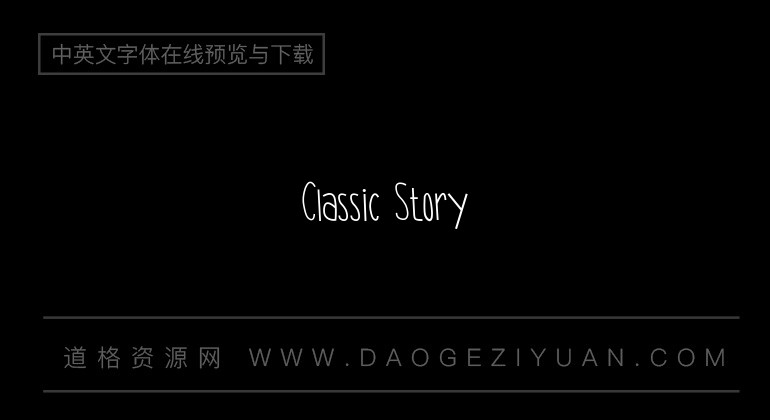
Classic Story 字体是一种优秀的手写风格字体,具有艺术性和可读性。 这种字体具有非常自然的手写风格,每个字母都具有独特的风格和形状,使其非常适合用于各种印刷和数字媒体设计项目。它的字母形状优美、流畅,同时还具有一定的装饰性,能够增强设计的美感和格调。 Classic Story 字体的特点还包括: - 多种字重和风格可选,能够满足不同设计需求。 - 适用于多种语言,包括英语、法语、西班牙语等。 - 与 Adobe Creative Suite 和 Microsoft Office 兼容,方便使用和编辑。 总之,Classic Story 字体是一种具有艺术性和实用性的字体,适用于各种设计项目,包括印刷品、标志、海报、网站、视频制作等。内容介绍
Classic Story是一款非常不错的手写艺术字体,具有很好的视觉感,适合于文化类的宣传设计、商业类品牌的广告和产品包装设计以及个性化文字排版等较多场景。